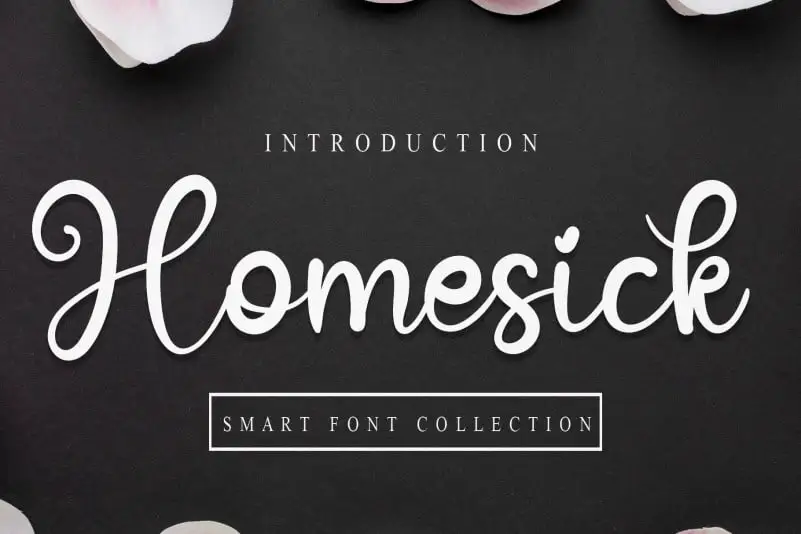
Homesick Script Font – Download Grátis
A fonte ‘Homesick Script Font’ é a escolha perfeita para quem busca uma experiência inovadora em projetos visuais criativos. Com seus traços delicados e gestualmente naturais, esta fonte cuidadosamente desenhada por CreativeLetter oferece um toque pessoal que se encaixa perfeitamente no estilo handwritten. Ela é a escolha ideal para texturas de websites únicas, publicações gráficas ou qualquer projeto onde uma escrita autêntica e original seja essencial. Seja você o criador que busca personalidade em seu trabalho ou o cliente profissional buscando qualidade e versatilidade em suas fontes digitais, a ‘Homesick Script Font’ está aqui para transformar seus projetos em obras de arte memoráveis.